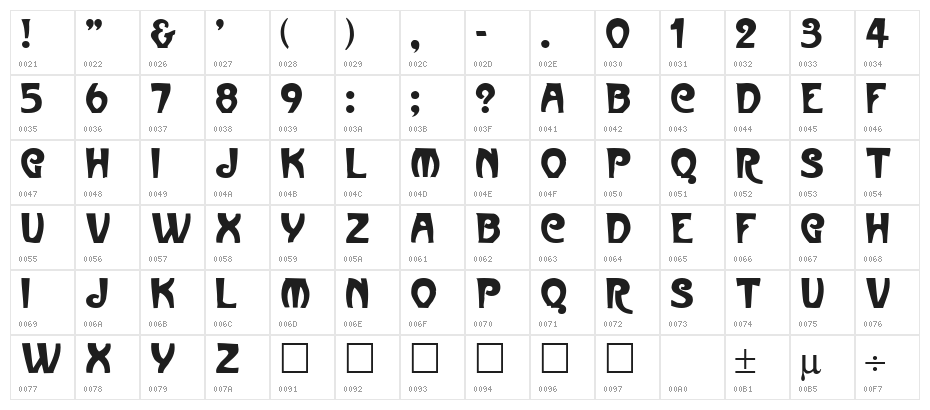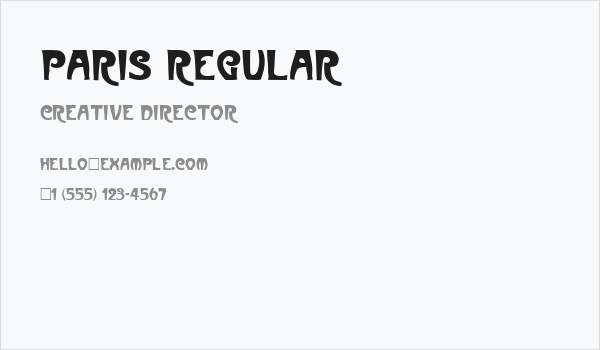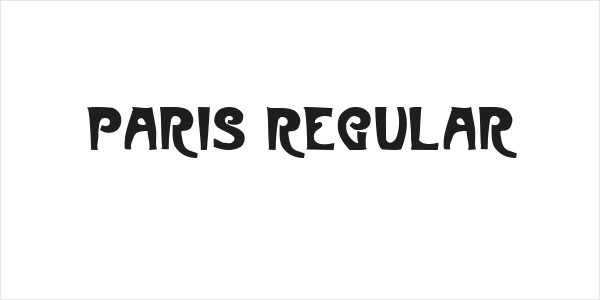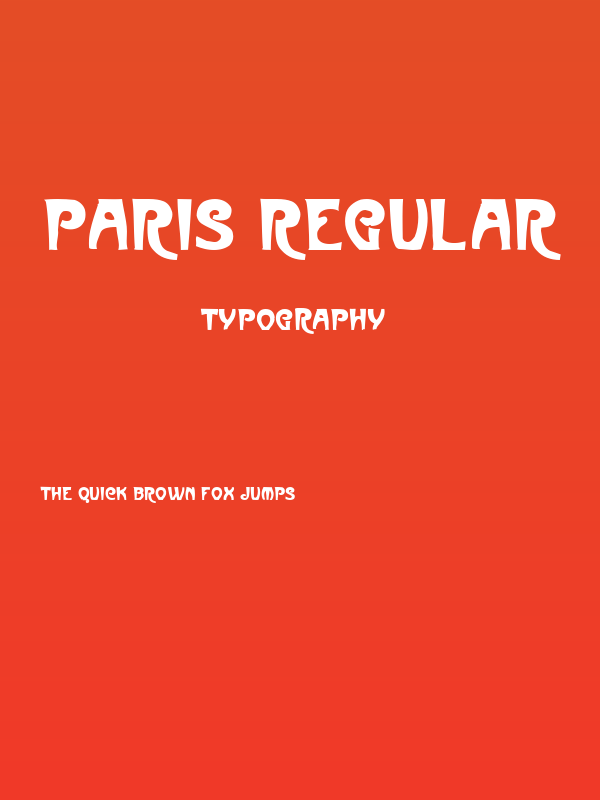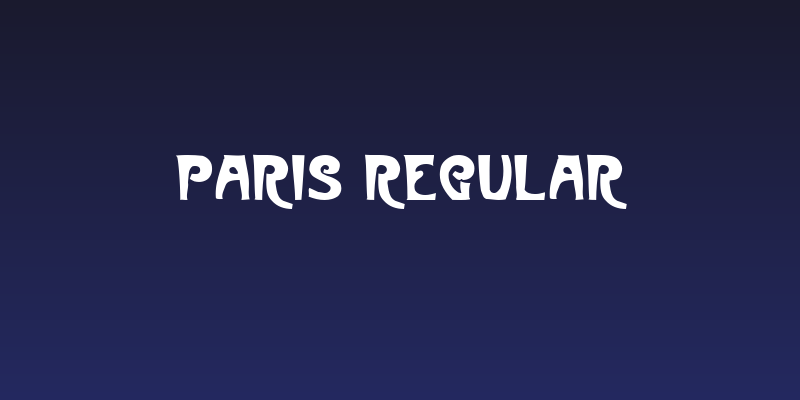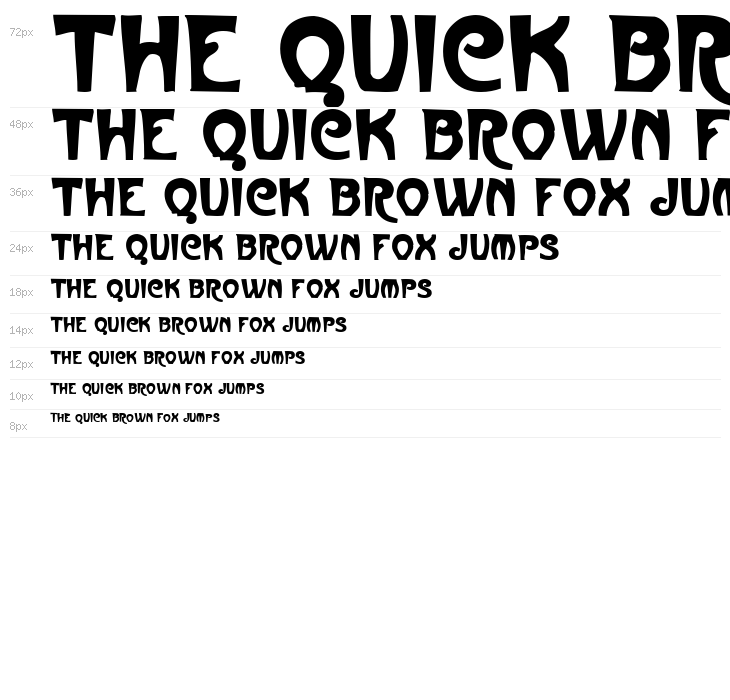
Paris Regular Font
| Vorgeschlagene Projekte | Ideal for posters, branding, headlines, and any design project that requires a bold and creative touch. |